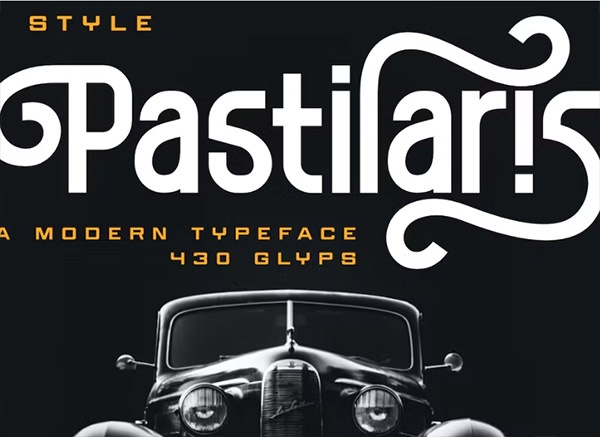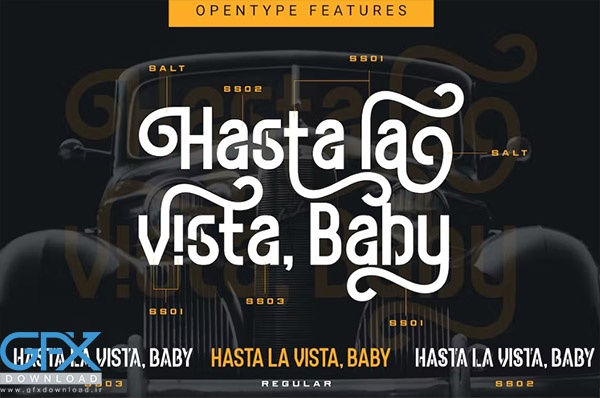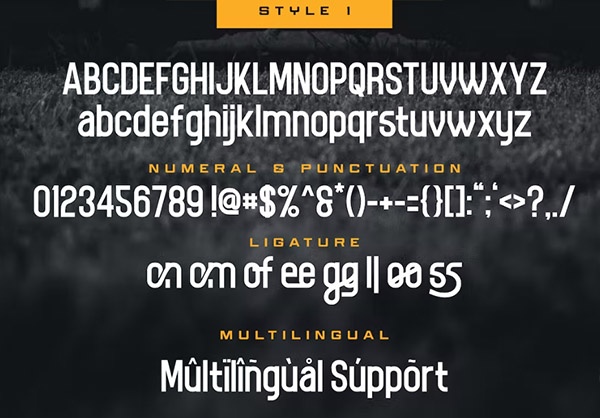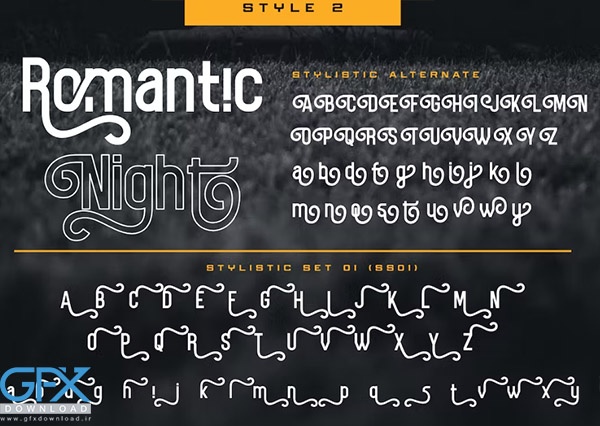
فونت رایگان لوکس مدرن Pastilaris
فونت انگلیسی رایگان لوکس مدرن Pastilaris
فونت رایگان لوکس مدرن Pastilaris یک فونت لوکس مدرن و زیبا که دارای 4 سبک است. فونتی که پروژه شما را زیبا می کند تا 430 گلیف مجهز شده است که البته انتخاب ها و تنوع طراحی زیادی خواهد داشت. فونت لوکس مدرن و زیبا برای طراحی، لوگوها، رسانه های اجتماعی، برندسازی، تبلیغات، طراحی محصول، عناوین مجلات، بسته بندی محصولات، سربرگ ها، پوسترها، کالاها و طرح های دیگر مناسب است.برای دانلود فونت رایگان به ادامه مطلب بروید.
• نام فونت: Pastilaris Modern
• 4 سبک تایپ فیس
• گلیف های استاندارد
• سبک جایگزین
• لیگاتور
• لهجه چند زبانه